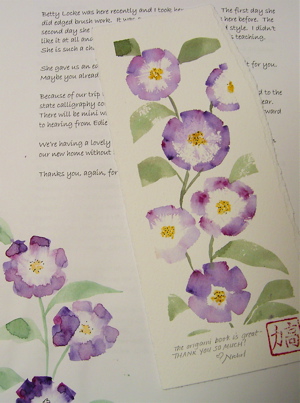
平筆のイラスト
お礼の手紙とカードは、得意の平筆によって花の絵が書いてありました。きれいですねー。どうやって平筆を使ったのか知りたいものです。花びらは平らに平筆を置いて、内側へシュッとかすれた線を出して書いているだけかもしれません。 今度試してみましょうね。
さて、お礼にということで彼女が取ったベティロークというカナダ人のワークショップのテキストが入っていました。私もアメリカにいる時に何度か彼女のクラスを取りましたが、平筆のマスターです。いろいろなアイデアと形がダントツに面白いのです。
特にこの部分、ハロウィーンのジャック-オ-ランタンとクモとタコみたいなゴーストが可愛いでしょう!?
ますますバージョンアップしていて、楽しくなります。
きっと描けないものなどないでしょうね〜〜。
よく見たら上の部分にA〜Zまで書いてありました。
これでけでもなーんて素敵!